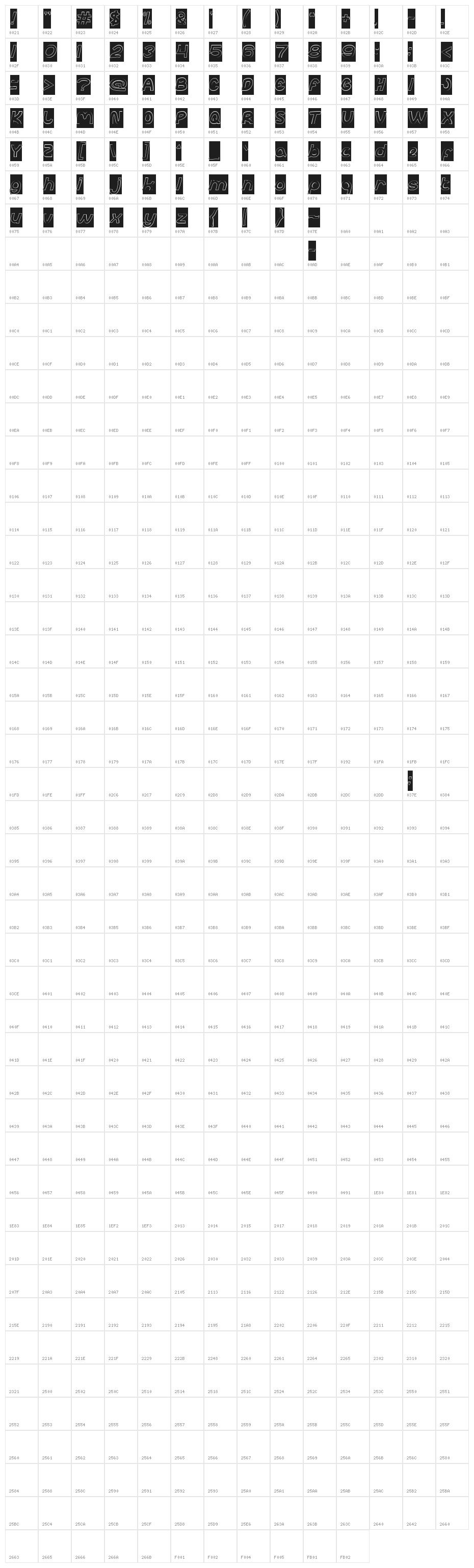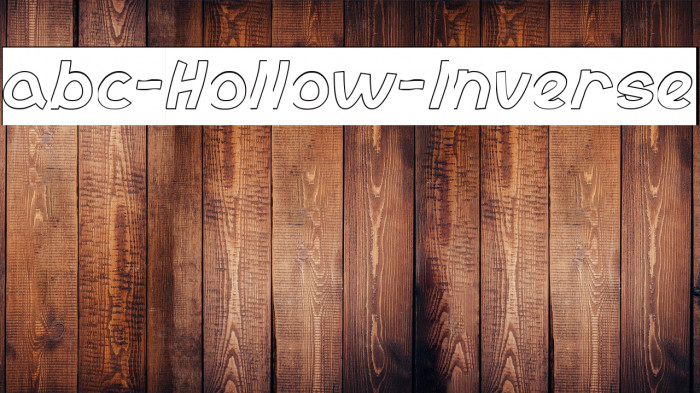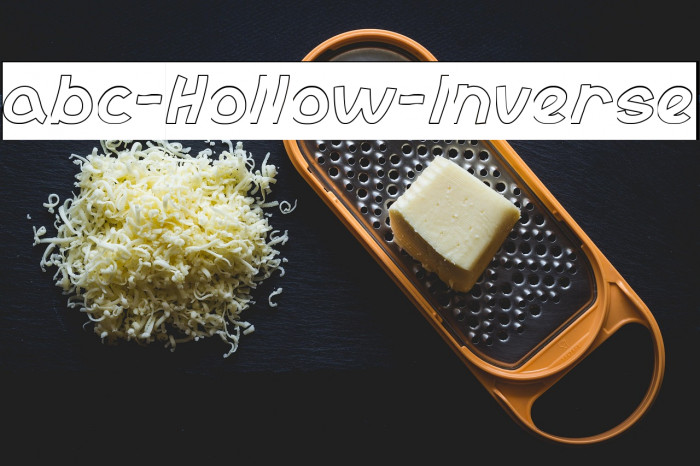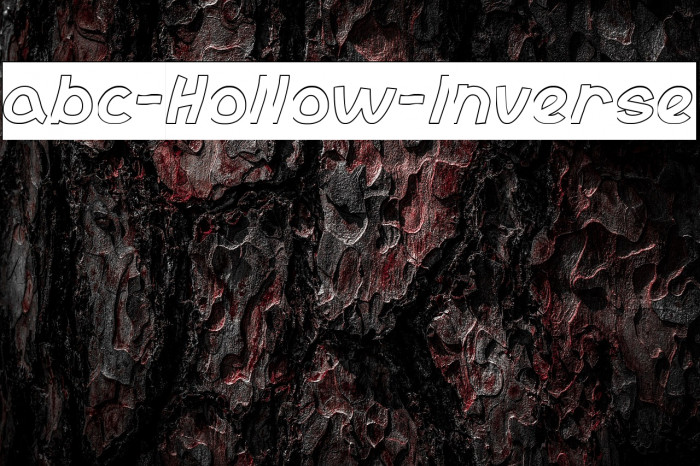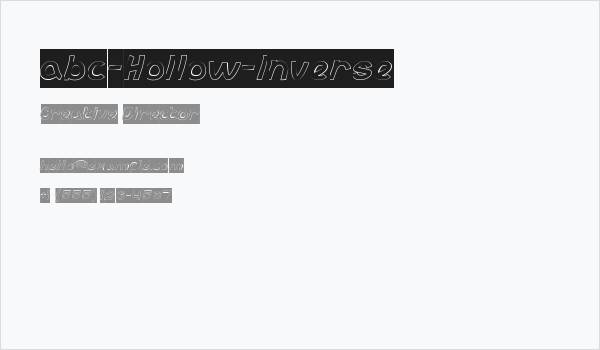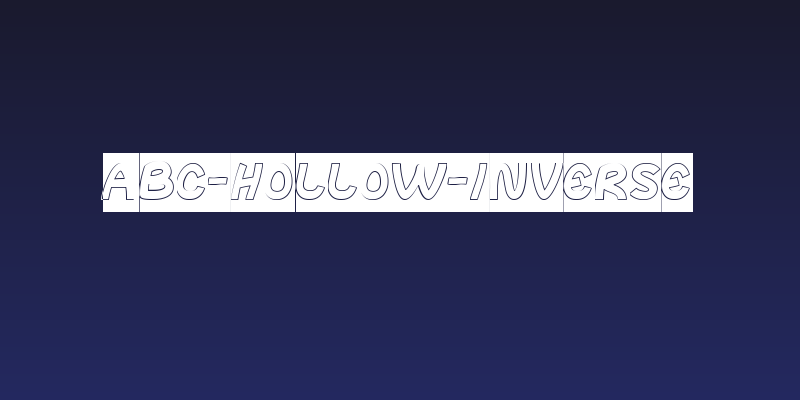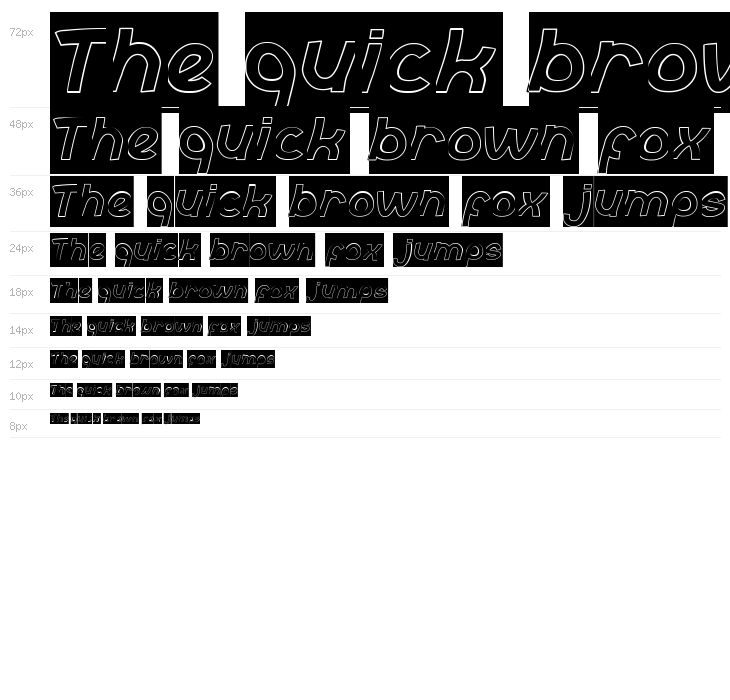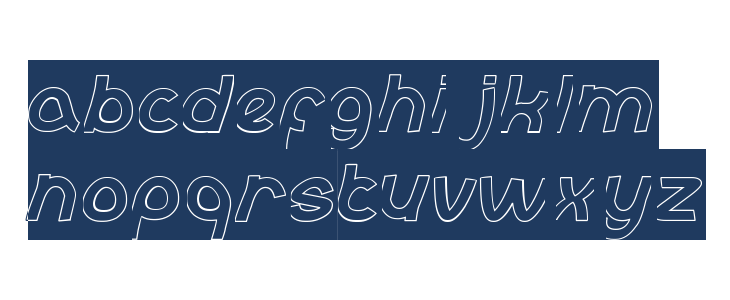
abc-Hollow-Inverse Font
| Рекомендуемые проекты | Ideal for creative projects such as posters, logos, and headlines where a bold and distinctive look is desired. |